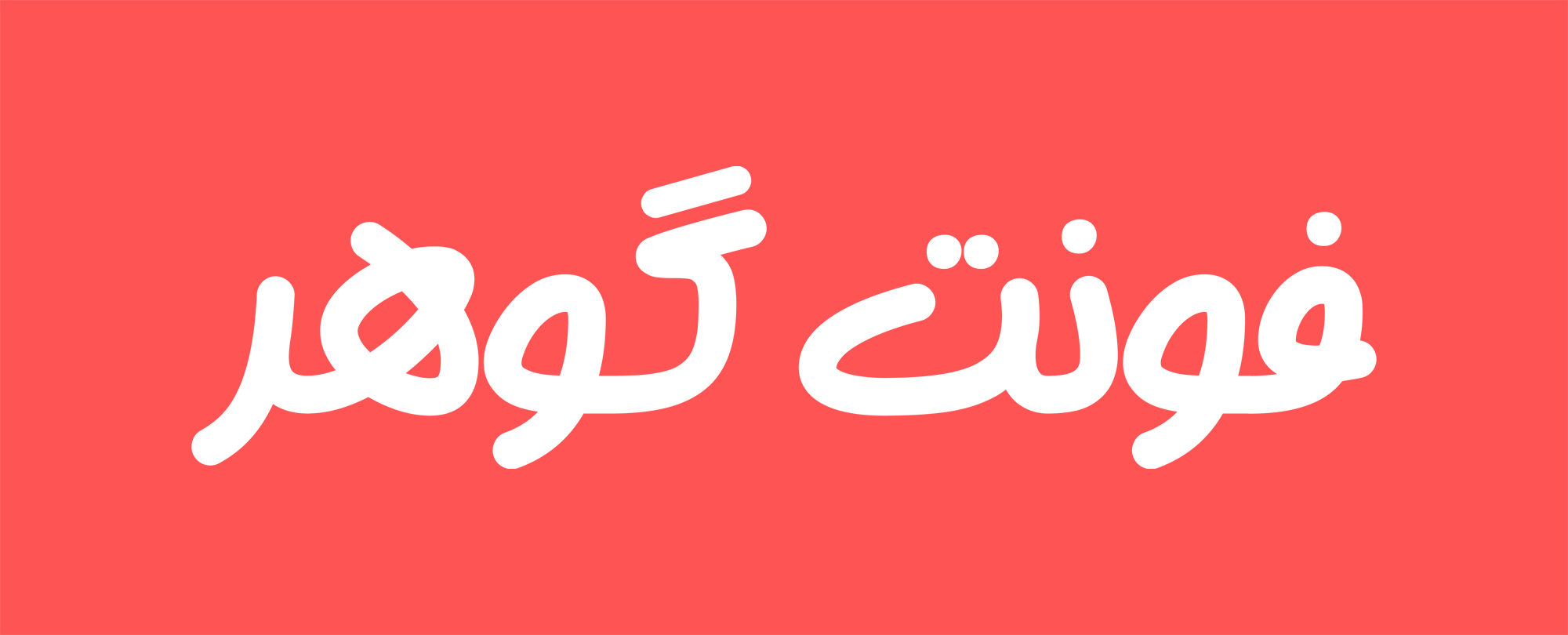
فونت گوهر
فونت گوهر یک فونت دست نویس ضخامت یکسان (منولاین) است که توسط مصطفی اوجی طراحی شده است. مصطفی اوجی طراح فونت گوهر از اولین طراحان تایپ ایران است که این حرفه‌ را به صورت آکادمیک آموخته است. مصطفی اوجی سال‌ها، استاد درس طراحی حروف در دانشگاه هنر تهران بوده است و تا کنون فونت‌های فارسی و عربی بسیاری را طراحی کرده است.
فونت گوهر ساختار فشرده و اصطلاحاً جمع و جور دارد برای همین سطرهای منسجم و فشرده‌ای ایجاد می‌کند. حرکات حروف به رغم رهایی حرکات قلم، فرم‌های کنترل شده‌ای‌ دارند.
فونت گوهر در ۵ وزن: نحیف، لایت، متوسط، بولد و سیاه طراحی و ارائه شده است که با کمک آن می‌توانید کنترل خوبی روی دسته بندی نوشته‌ها داشته باشید.
در ادامه می‌توانید نمونه‌ متن‌هایی از فونت گوهر را ببینید:
فونت گوهر
فونت فارسی گوهر تایپ فیسی ماژیکی است که امروزه بسیار محبوب و رایج است و طراحان از این فونت استفاده می نمایند. این فونت با فرمت ttf طراحی و ساخته شده است و قابل نصب روی تمامی برنامه هایی که امکان تایپ فارسی با انها وجود دارد میباشد.